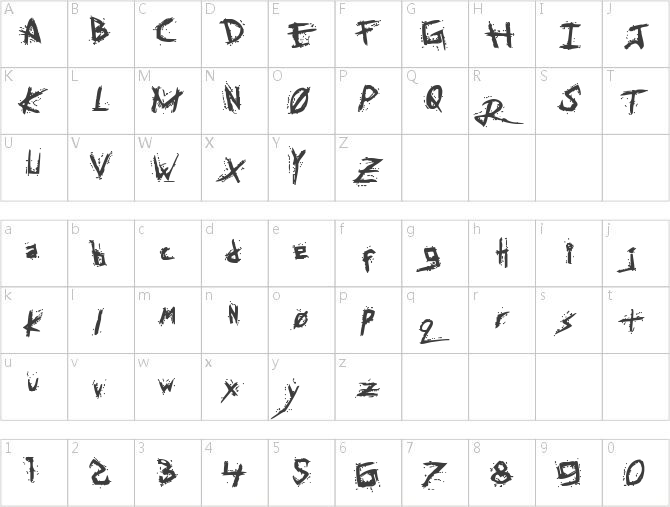
assassinnationextrabold
assassinnationextrabold介紹
assassinnationextrabold字體字庫是一款讓人賞心悅目、百看不厭的英文字體,適合各類廣告和產品包裝設計應用,字體大小0.19MB,格式為ttf字體,上傳用戶是韓國露韓,作者/版權方為未知